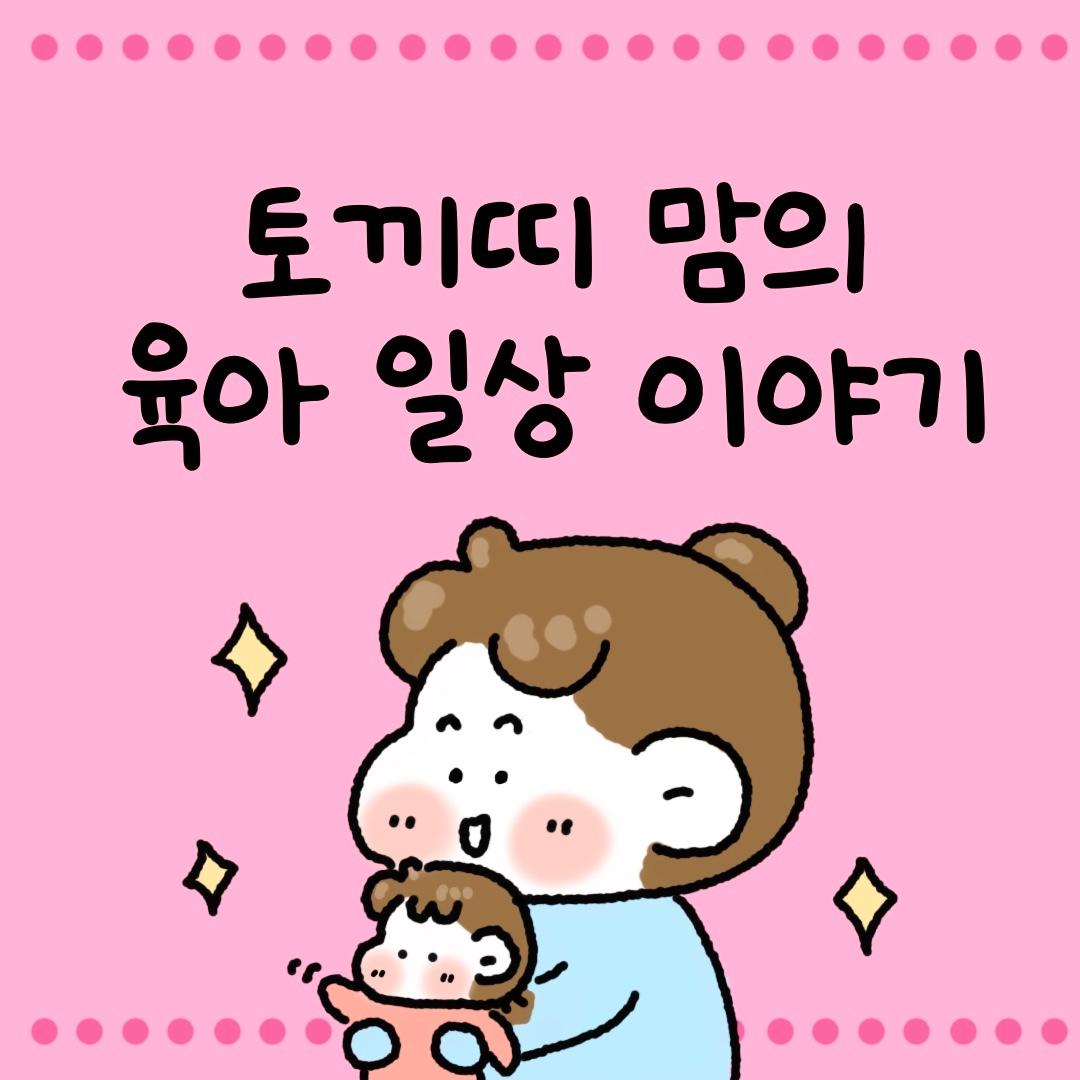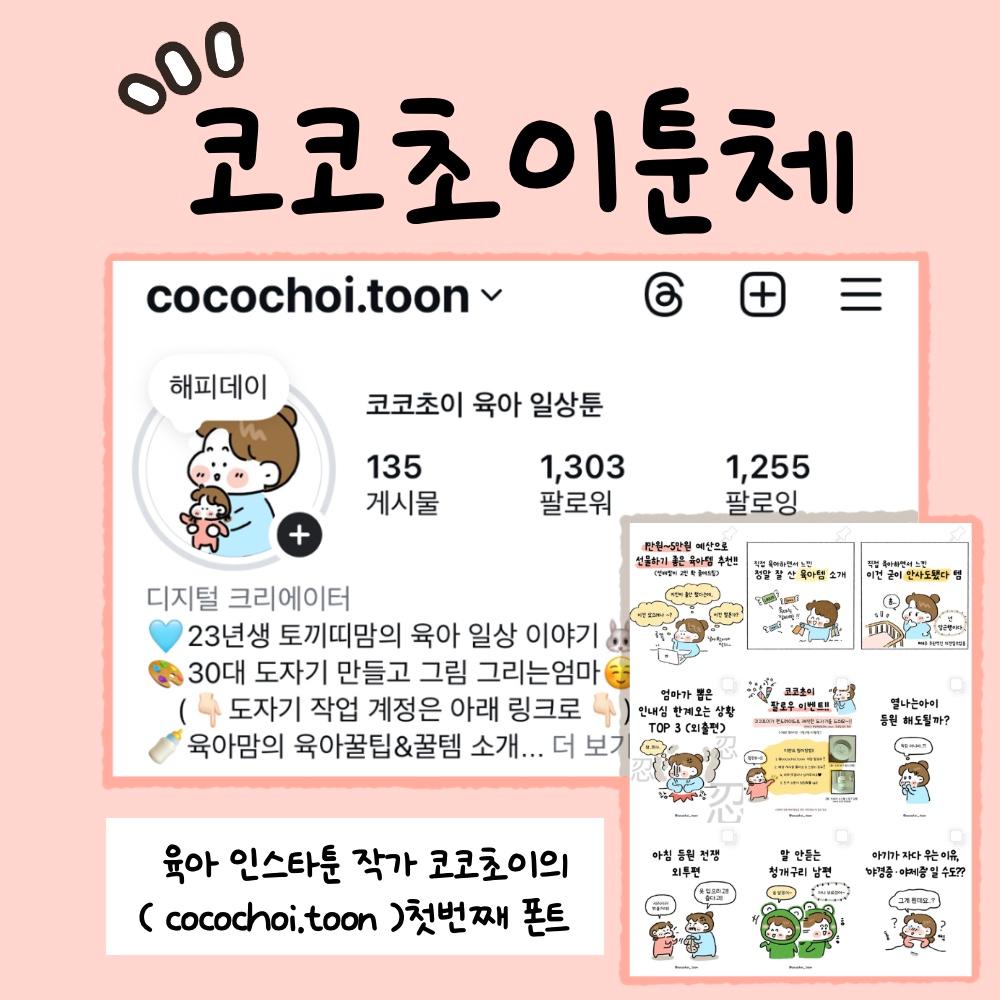
그리운 코코초이툰
Griun Cocochoitoon
그리운 코코초이툰 소개
그리운 코코초이툰(Griun Cocochoi Toon)은 육아 인스타툰 작가로 활동하며 매일의 육아 순간을 기록하는 과정에서 자연스럽게 만들어온 저만의 손글씨 느낌을 그대로 담은 폰트입니다. 육아툰을 통해 다양한 분들과 소통할 수 있었던 시간이 너무 행복했고, 그 따뜻한 감정을 글씨에 담고 싶었습니다. “이 글씨체로 더 많은 분들이 자신의 이야기를 표현하면 좋겠다”는 마음으로 하나하나 직접 손으로 써 제작했어요. 코코초이툰체는 인스타툰, 메모, 다이어리, 손글씨 이미지 제작 등 일상 곳곳에서 편하게 사용할 수 있도록 가독성과 아기자기함을 모두 갖춘 글씨체입니다. 이 폰트가 여러분의 하루에 조금 더 웃음과 온기를 더해주길 바랍니다 :)